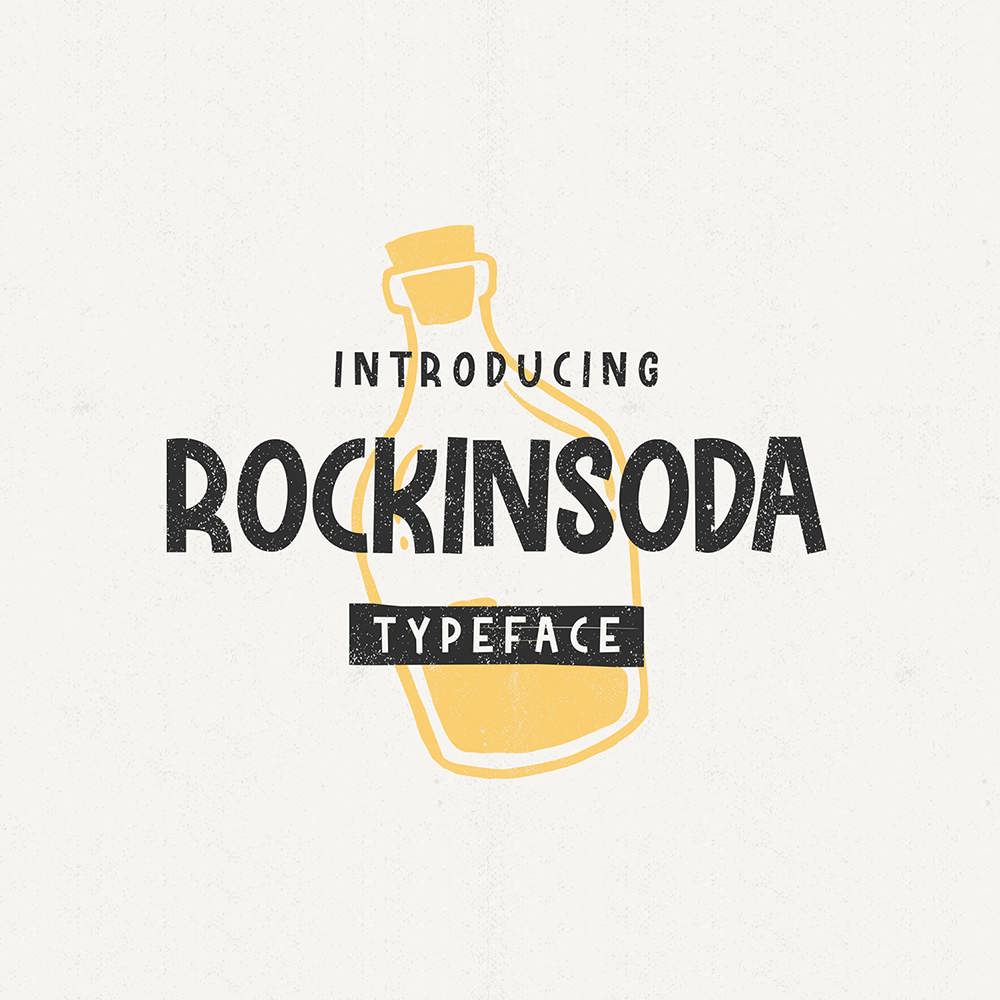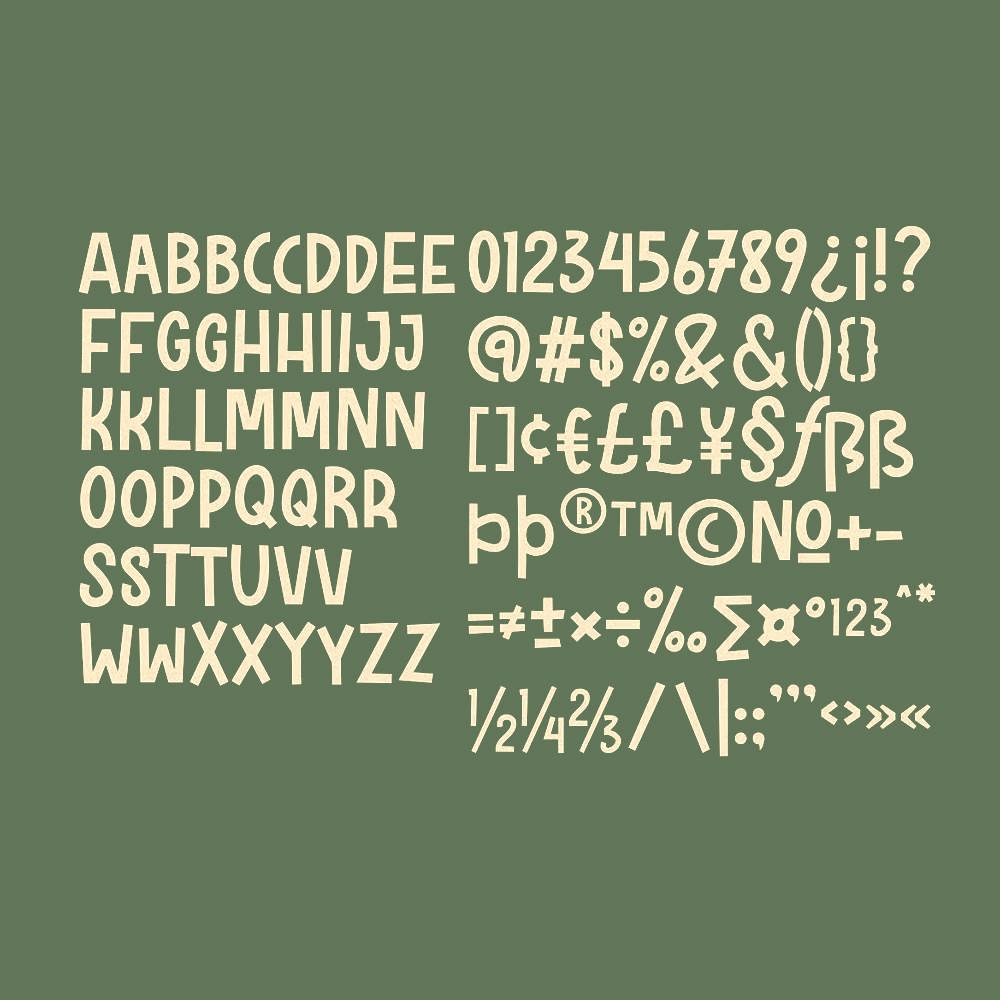
فونت پرمیوم و انگلیسی Rockinsoda Font یک فونت نمایشی با سبک دستخط کودکانه است که در حالت حروف بزرگ، بداههپردازی کمی دارد، اگرچه همه این فونتها حروف بزرگ هستند. این فونت همچنین دارای حروف کوچک متناوب است که میتواند برای حرف آخر یا جلد کلمه استفاده شود. این فونت برای هر چیزی که مربوط به غذا، کودکان، تصاویر کودکان، عناوین کتاب، عنوان وبسایت، نوشتن ویدیو یا هر چیزی که ممکن است بخواهید برای کسب تجربه در نیازهای طراحی گرافیک امتحان کنید، عالی است.